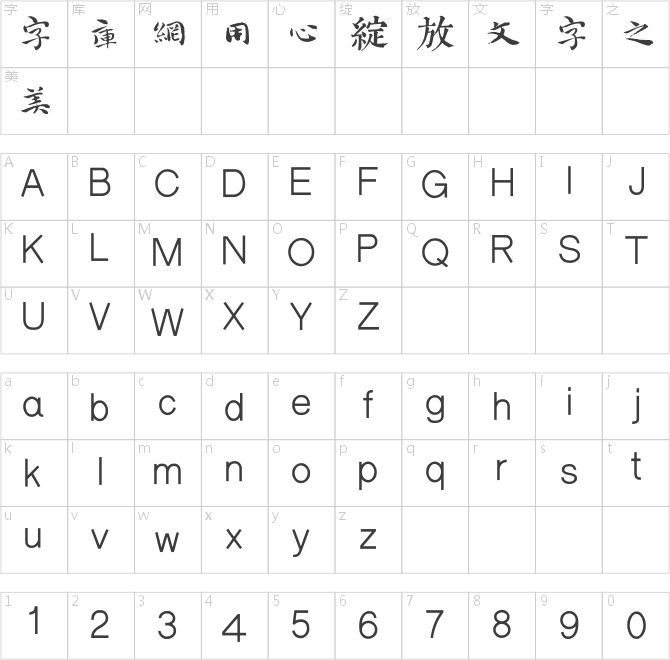
邯郸祝允明千字文 详情页
字体名称: 邯郸祝允明千字
邯郸祝允明千字文
邯郸祝允明千字文字体下载邯郸(明)祝允明千字文
注:本字库为古籍千字文复刻书法小字库,字符数量为1000余字,如有特殊需求,可以联系邯郸字库韩绍杰为您订制,也可以联系本站客服为您转答!
祝允明(1461年1月17日-1527年1月28日)生于天顺四年十二月六日,卒于嘉靖五年十二月二十七日,字希哲,长洲(今江苏吴县)人,因长像奇特,而自嘲丑陋,又因右手有枝生手指,故自号枝山,世人称为“祝京兆”,明代著名书法家。 祝允明的科举仕途颇为坎坷,十九岁中秀才,五次参加乡试,才于明弘治五年(1492)中举,后七次参加会试不第。甚至其子祝续也在前一科中进士,于是祝允明绝了科举念头,以举人选官,在正德九年(1514),授为广东兴宁县知县,嘉靖元年(1522),转任为应天(今南京)府通判,不久称病还乡。 祝允明擅诗文,尤工书法,名动海内。他与唐寅、文徵明、徐祯卿并称“吴中四才子”。又与文徵明、王宠同为明中期书家之代表。楷书早年精谨,师法赵孟頫、褚遂良,并从欧、虞而直追“二王”。草书师法李邕、黄庭坚、米芾,功力深厚,晚年尤重变化,风骨烂熳。北京大学教授、引碑入草开创者的李志敏评价:“祝枝山的狂草,骨力弱于旭、素,但在宋人影响下,又自成一格”。  其代表作有《太湖诗卷》《箜篌引》《赤壁赋》等。所书“六体书诗赋卷”“草书杜甫诗卷”“古诗十九首”“草书唐人诗卷”及“草书诗翰卷”等皆为传世墨宝。